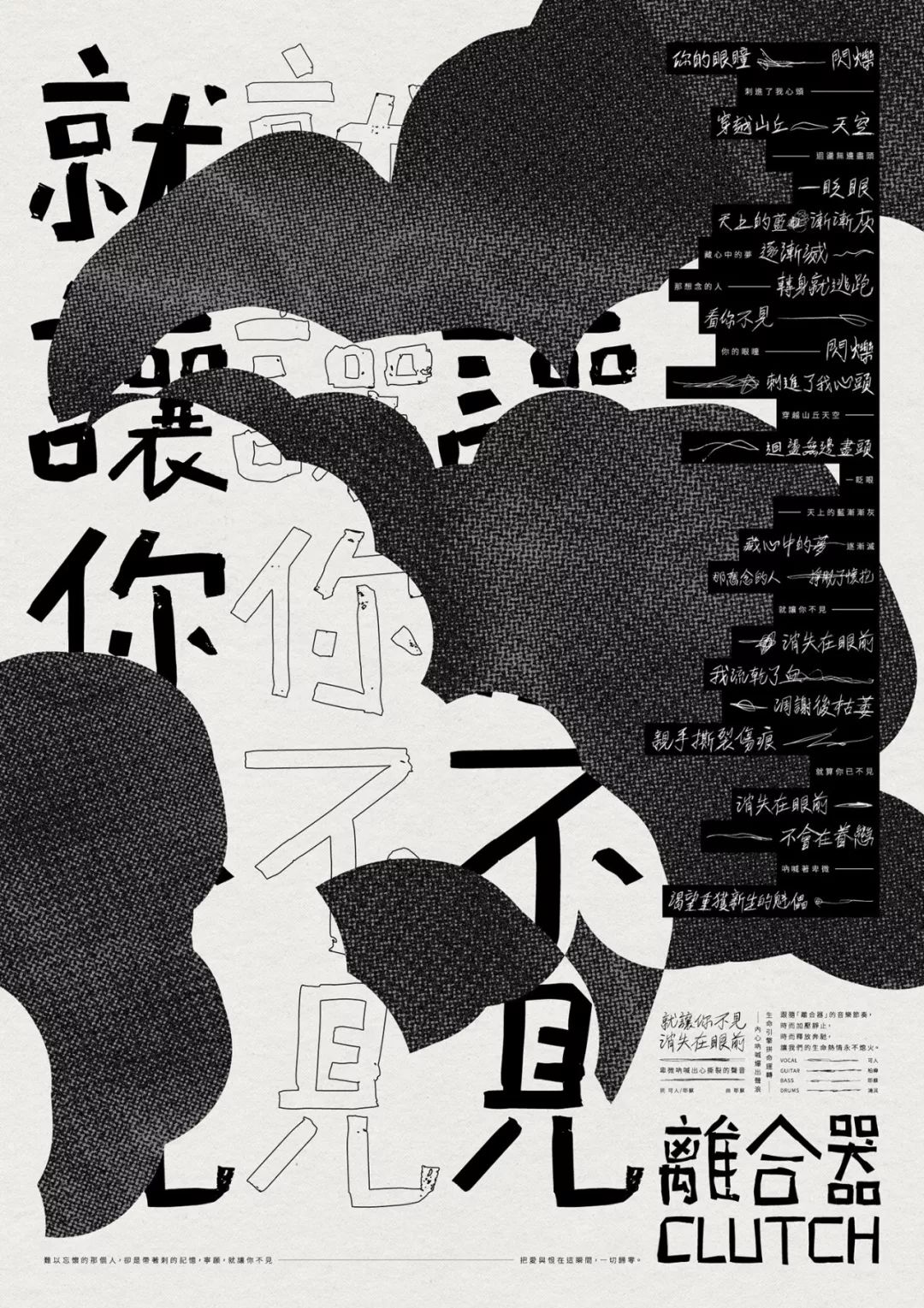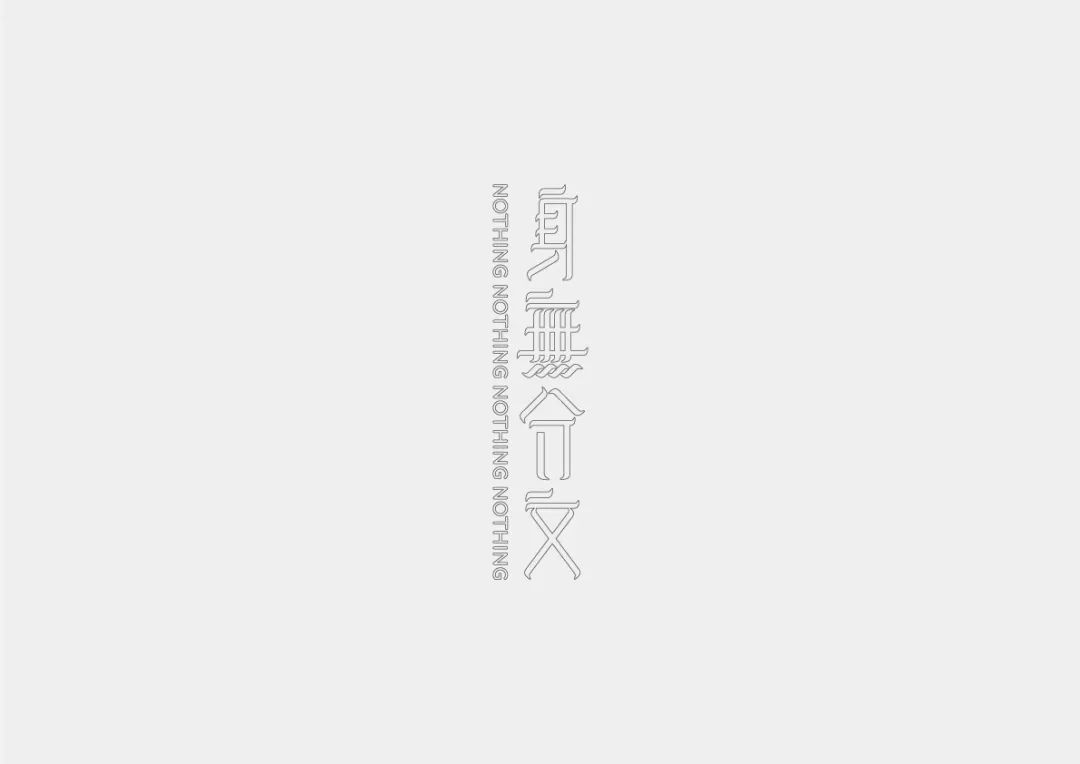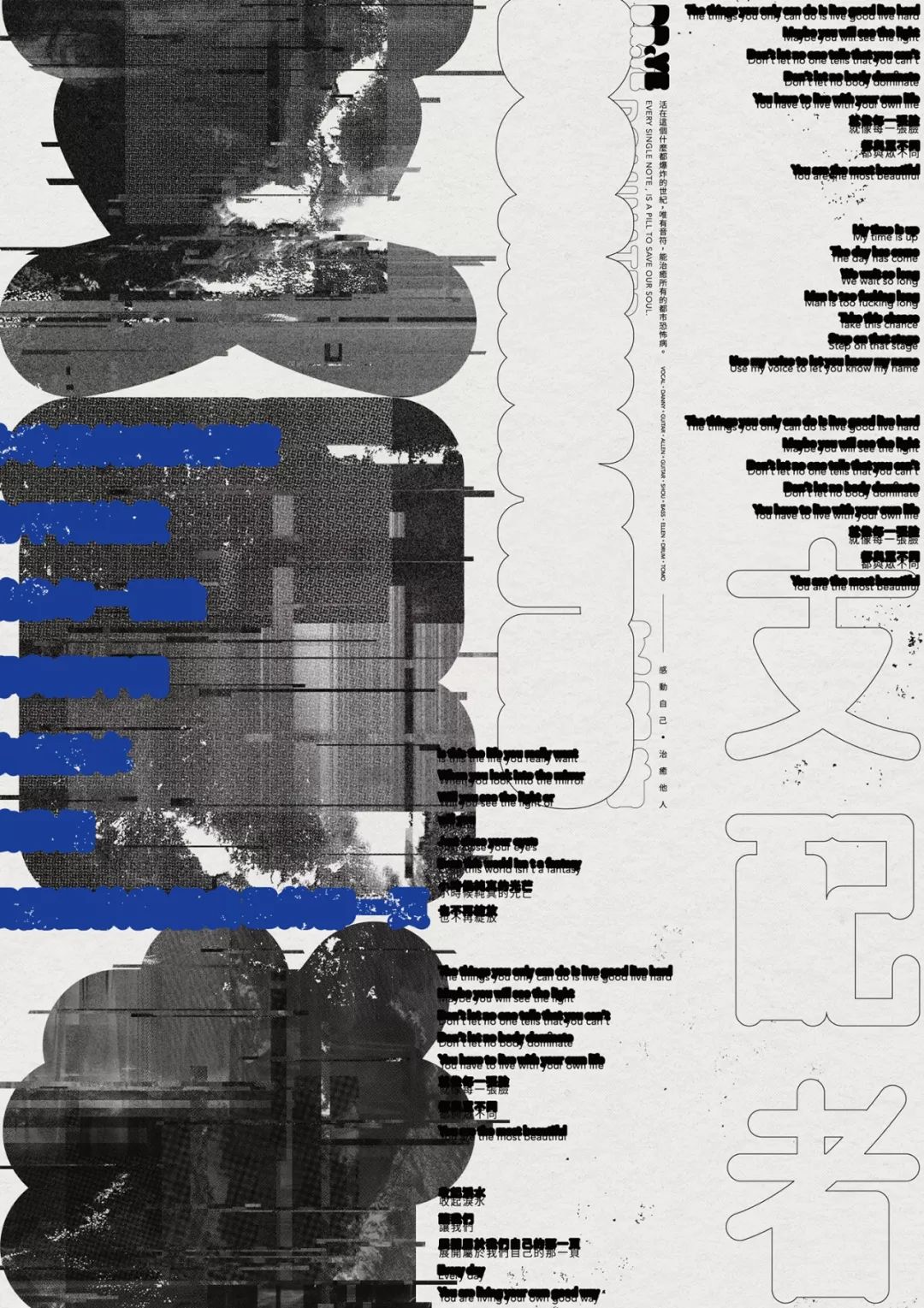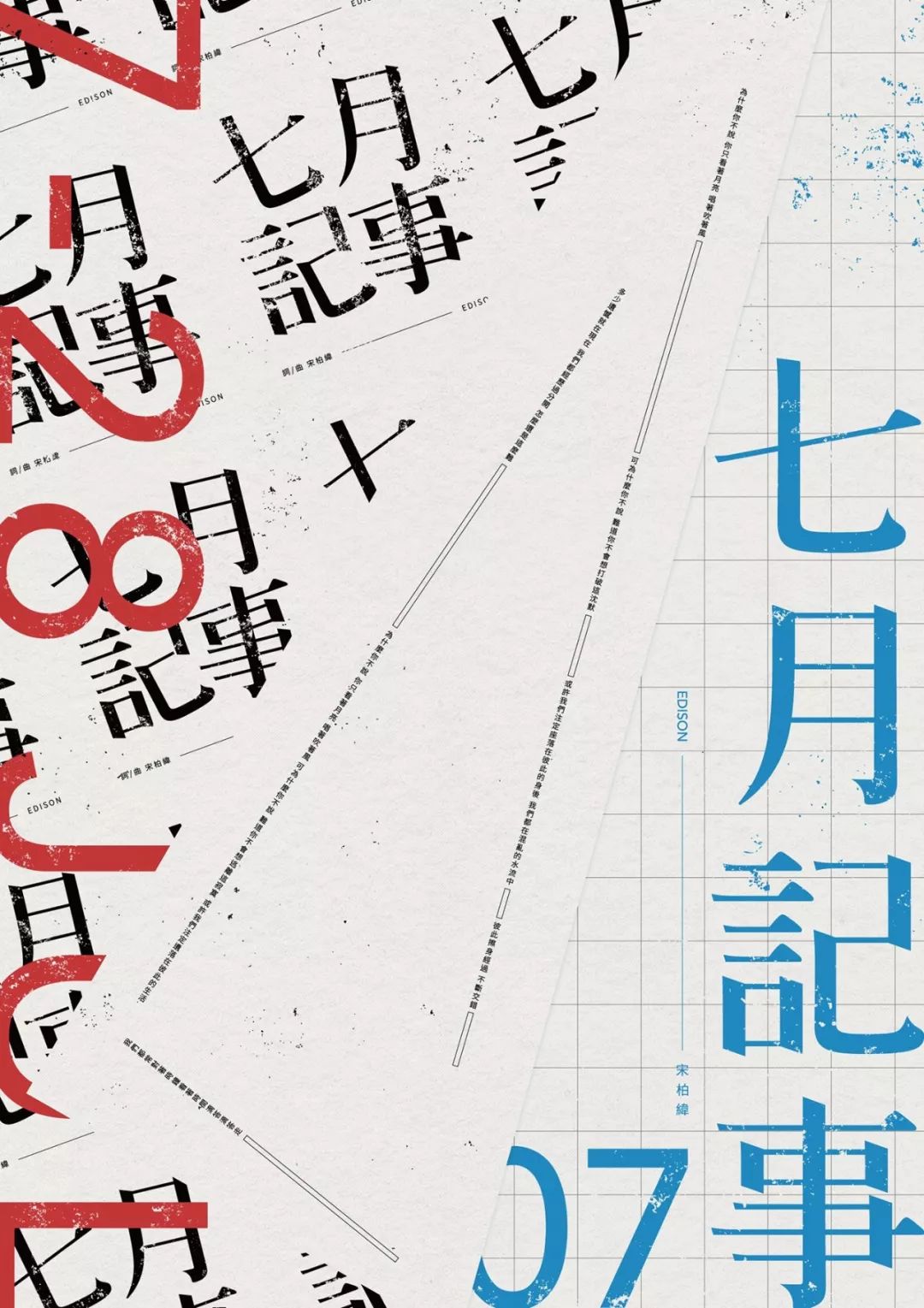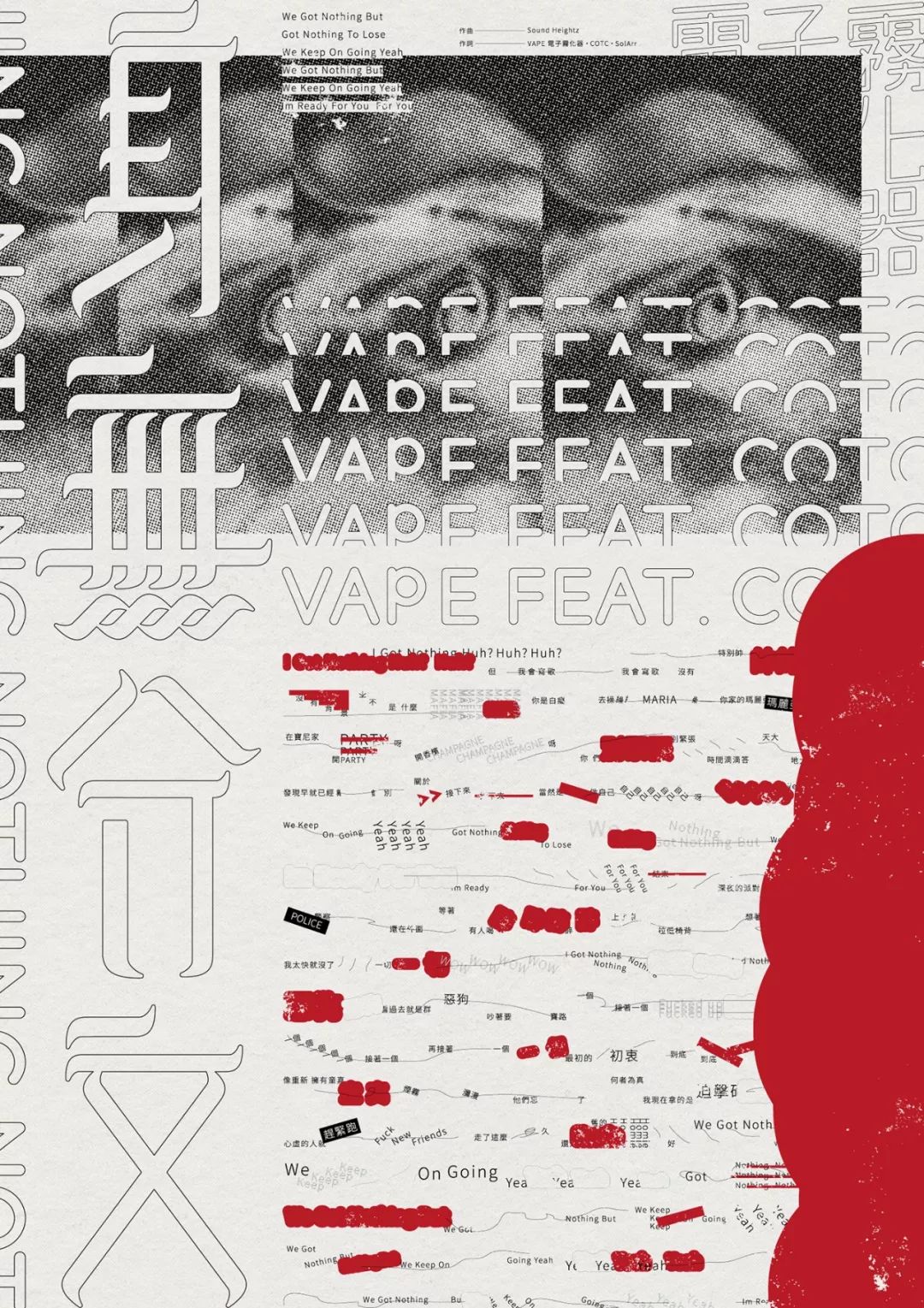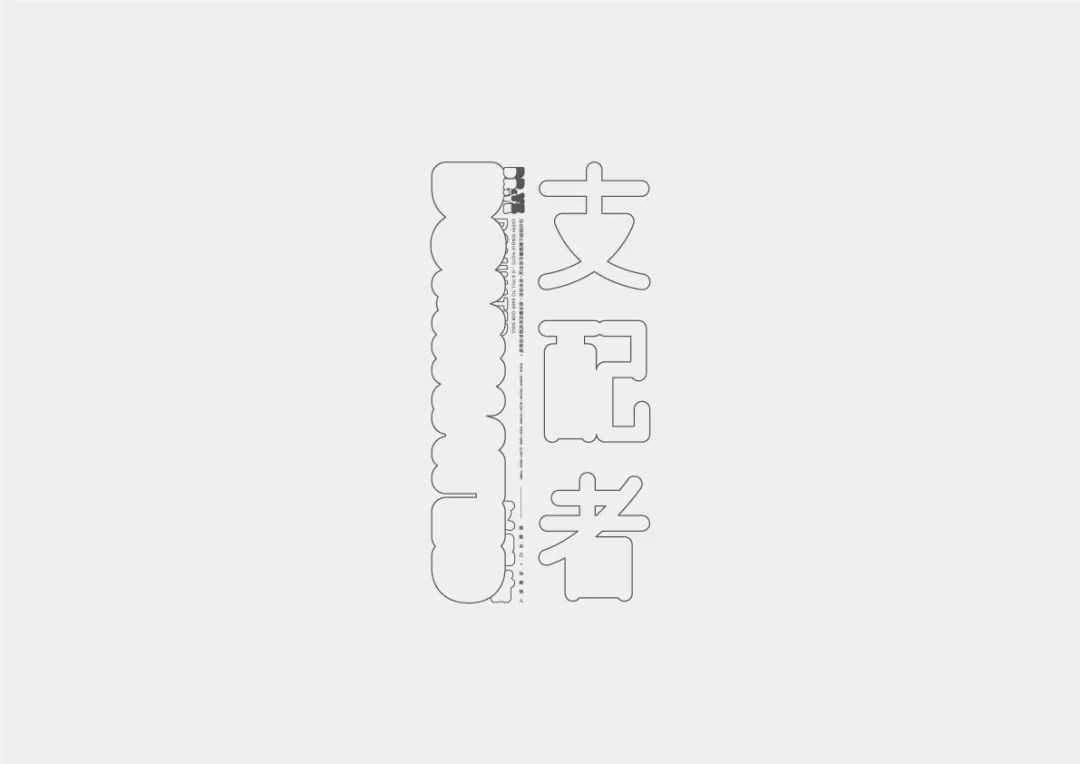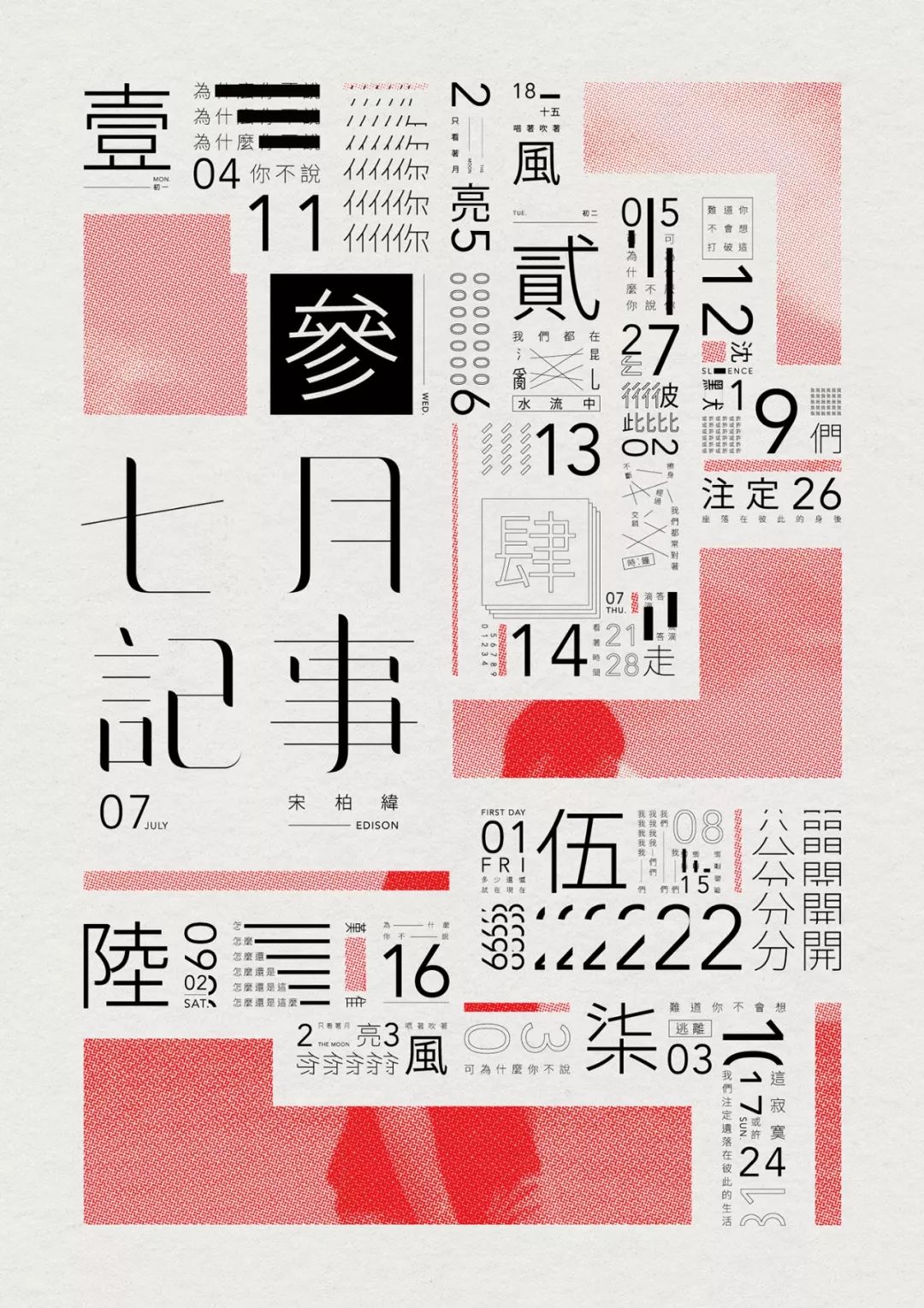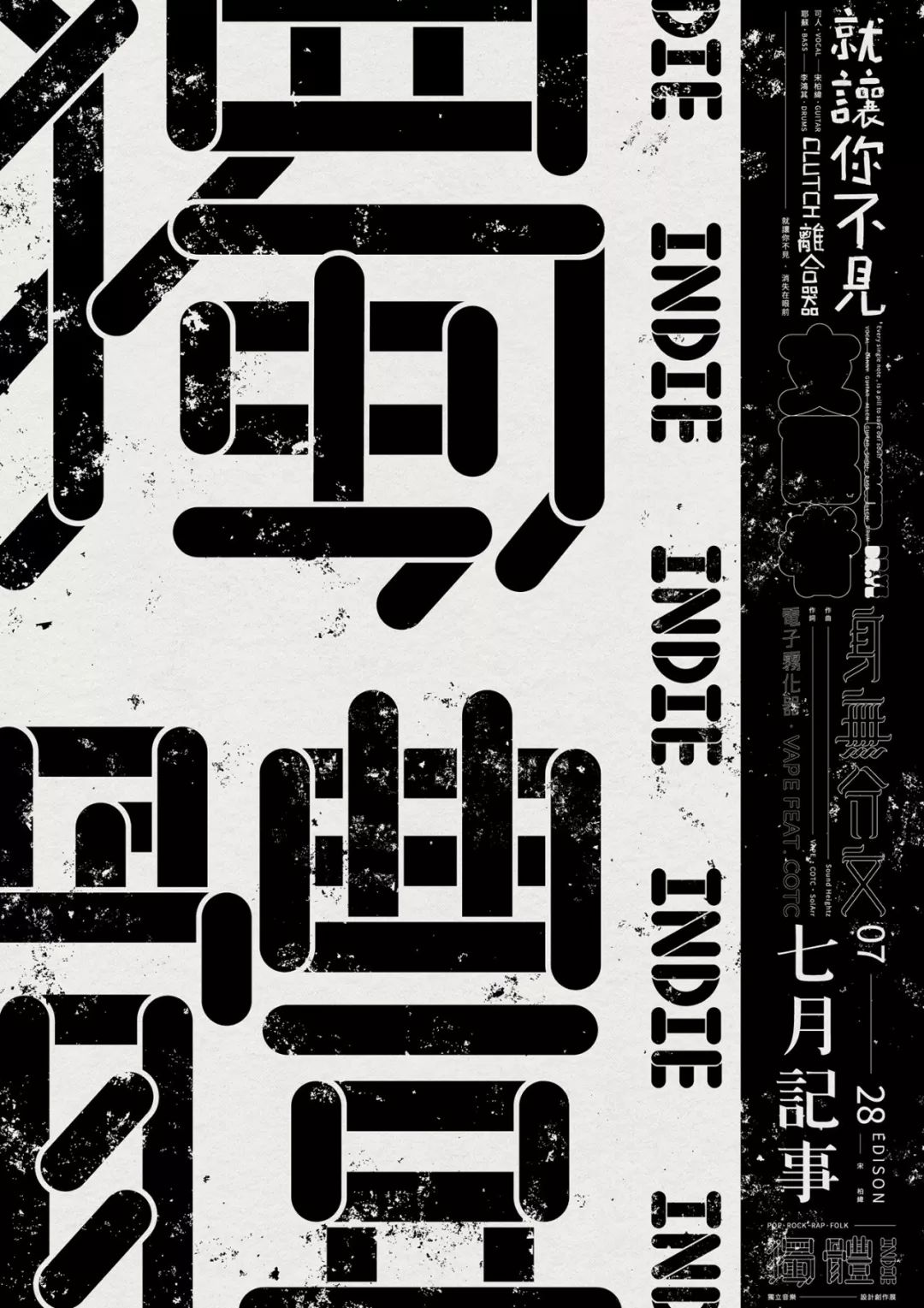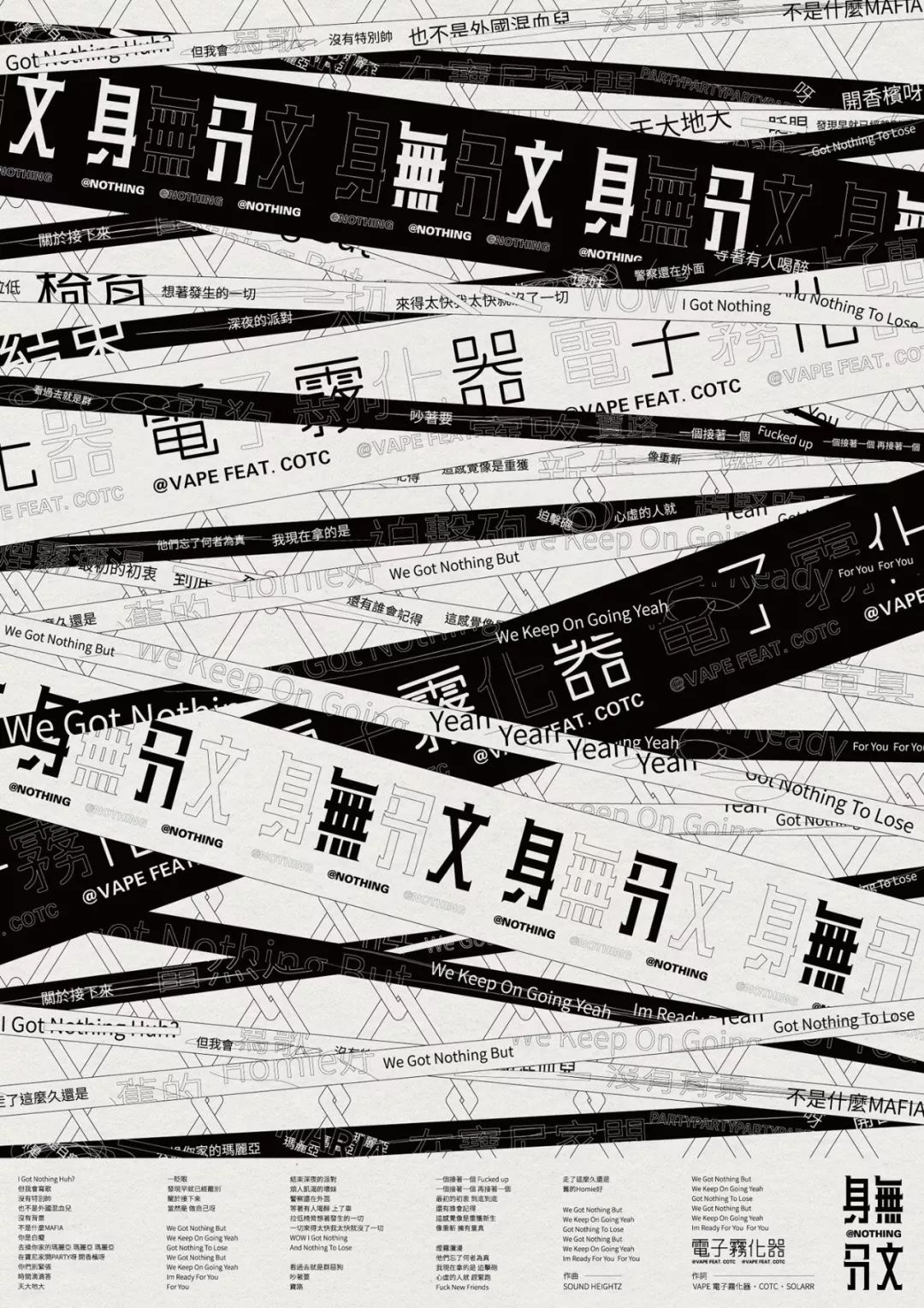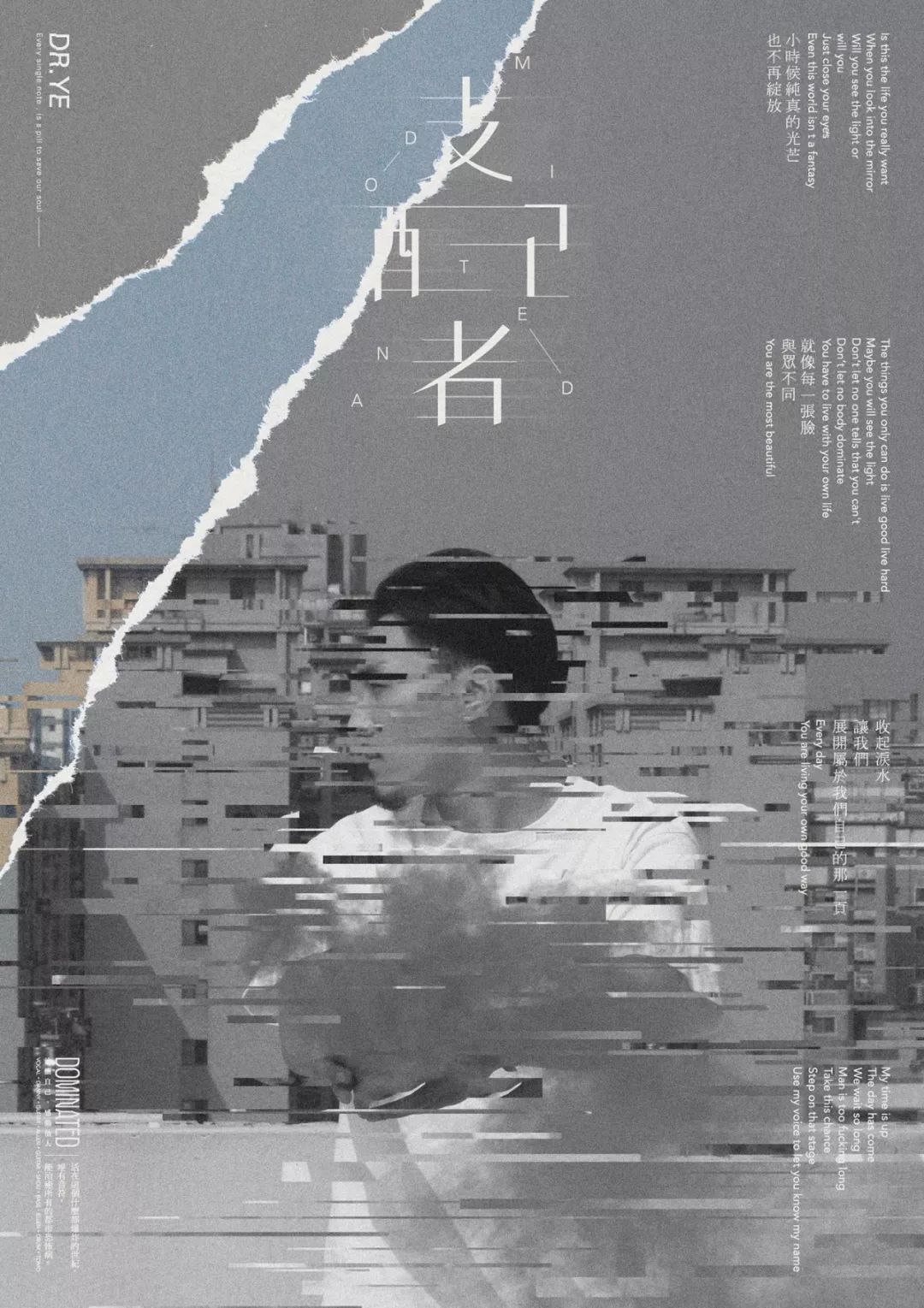
独立音乐视觉设计案例分享,给你灵感
今天,和大家介绍一位来自台湾设计师 Letitia Lin 的实验性中文字型创作作品:以独立音乐视觉设计为例。希望在字体设计的选择与设计应用上,能给大家带来灵感。
Experimental Chinese Typography - Taiwan Indie Music
「独体」 ・ 独立音乐创作合辑
运用音乐四种曲风(流行、摇滚、嘻哈、民谣)的外在特性,透过各种实验手法,将传统中文字体所蕴含的美学概念,以笔画的规律性去重新编排与设计,体现中文字型的美感与时代感,再以不同的媒材与技术,呈现具实验性(Experimental)的独立音乐视觉创作。
「独体」创作合辑,是以实际公开发表过音乐单曲的独立创作人,分别为三个音乐团体(流行曲风、摇滚曲风、嘻哈曲风)及一位创作人(民谣曲风),以四首不同曲风的单曲,结合四大类字型设计的表现手法(手写类、变形类、装饰美术类、原形类),将个别曲风的音乐创作,运用两种字型设计的表现形式于个别单曲的视觉海报及专辑歌词卡,呈现中文字型视觉创作的多变性及实验性的艺术特性。
Type : Music Poster / Album
Music : 离合器(CLUTCH)、DR.YE、VAPE、宋柏纬(EDISON)
Design : Letitia Lin
Poster Size : 594*841 mm
Album Size : 140*140 mm